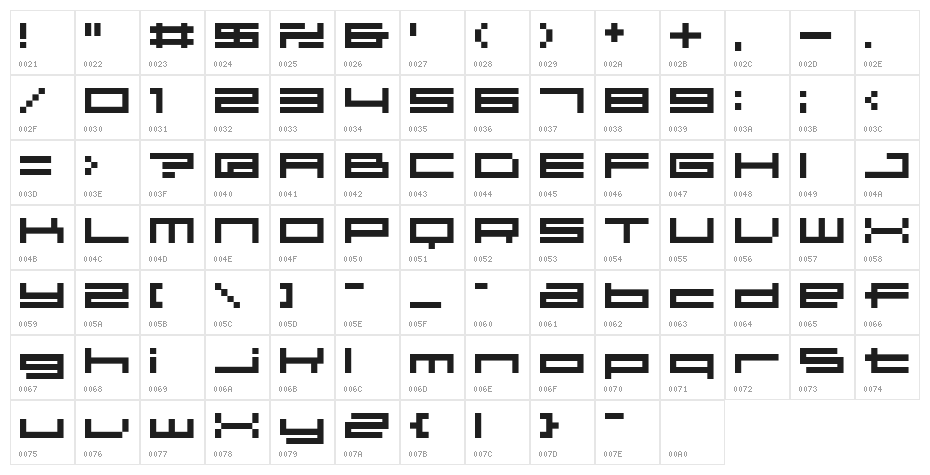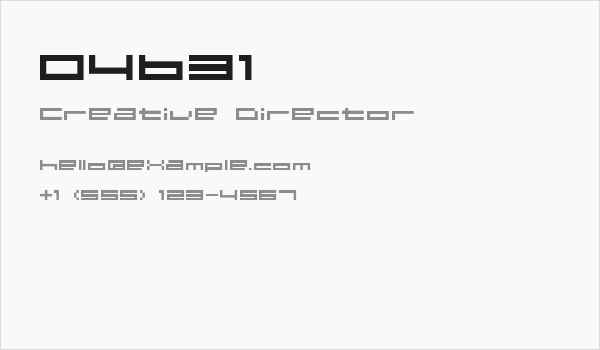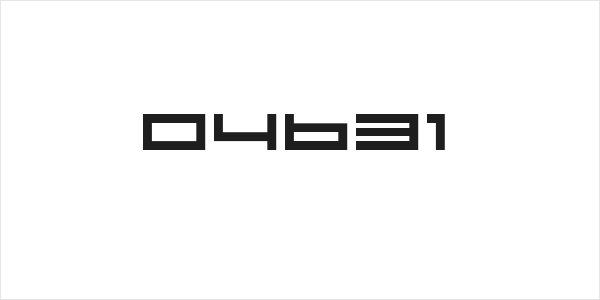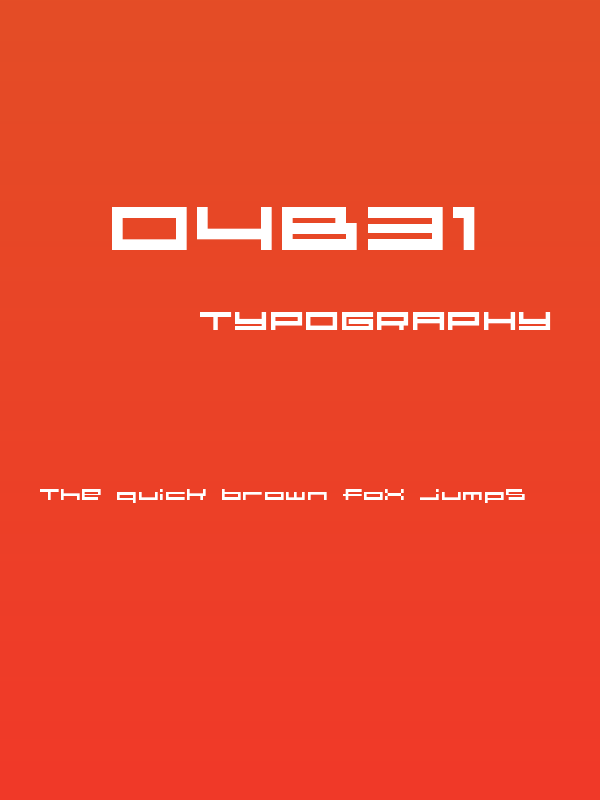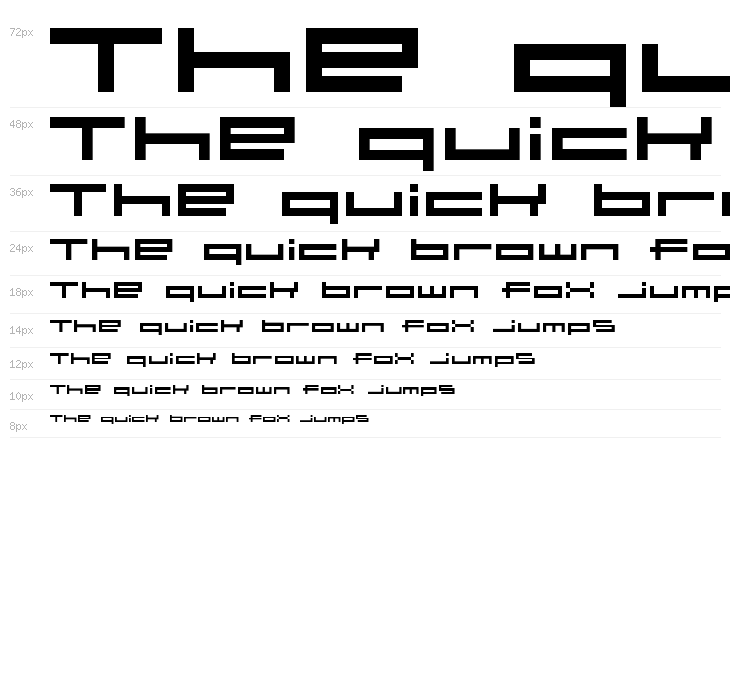
04b31 Font
| Kategorien | Pixel |
| Gesamtstil | Retro, Digital |
| Anwendungsfall | Logos, Headlines, Digital interfaces |
| Vorgeschlagene Projekte | Ideal for video game design, retro-themed posters, digital art projects, and tech-related branding. |